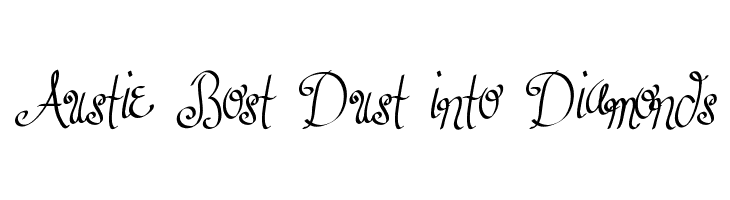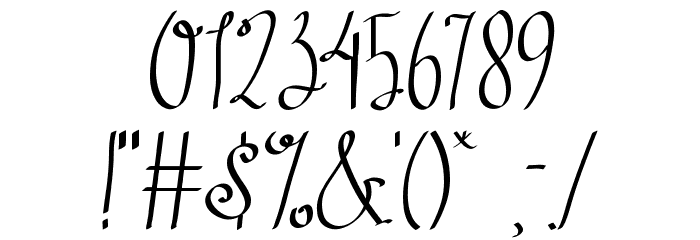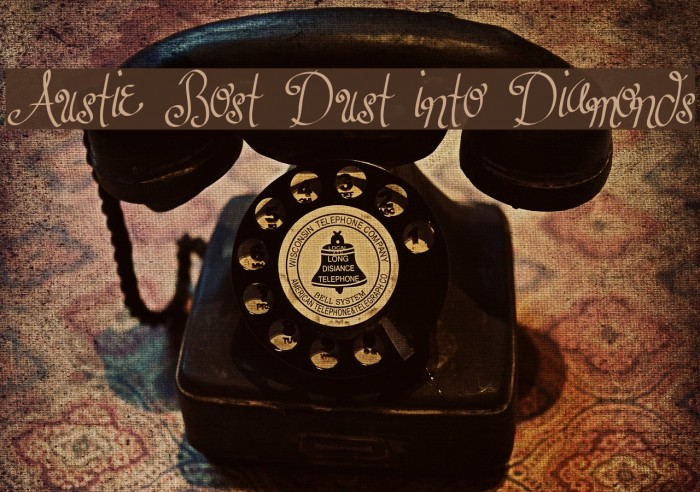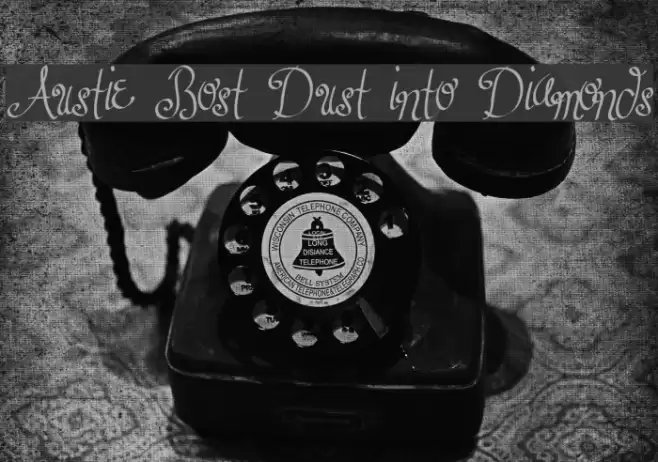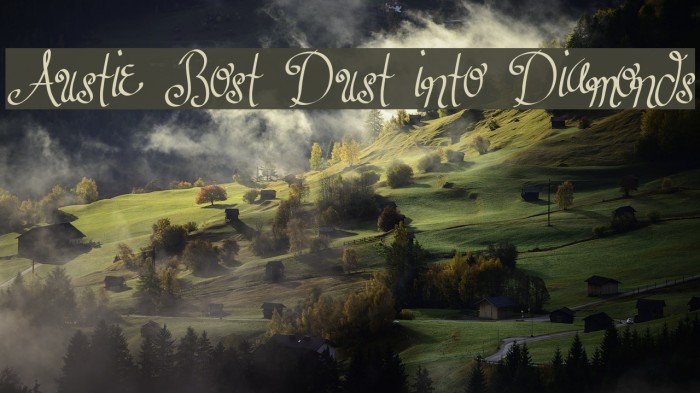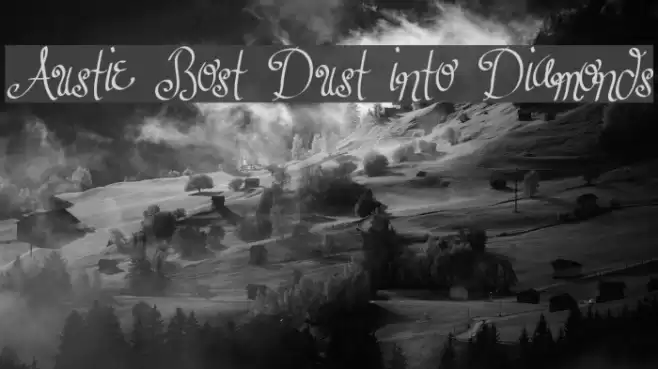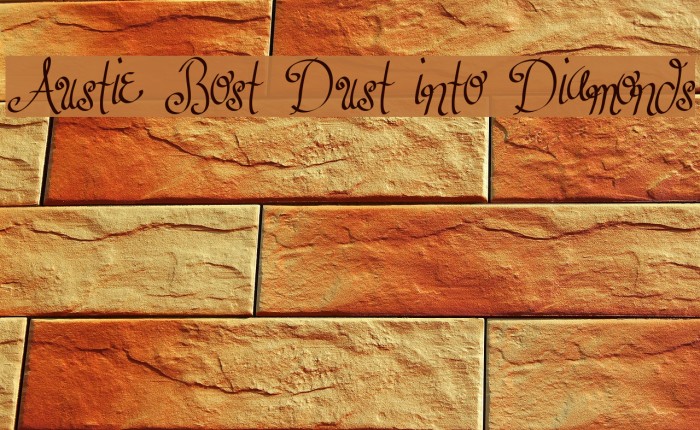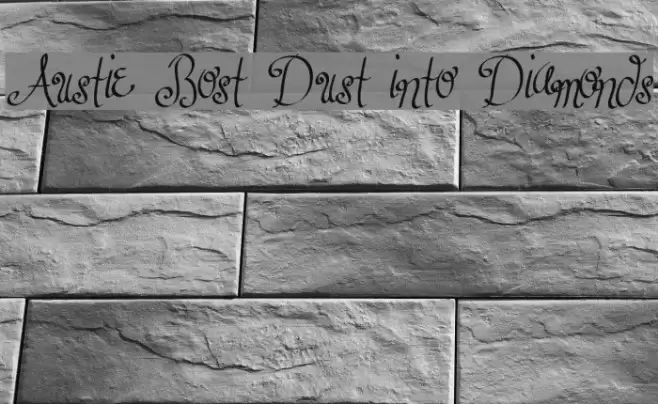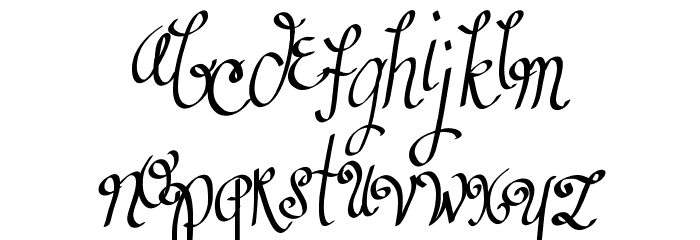
Austie Bost Dust into Diamonds Font
✎ Curly
| Kategorien | Curly |
| Anwendungsfall | Headlines, Logos, Invitations |
| Vorgeschlagene Projekte | Ideal for wedding invitations, greeting cards, playful branding, and artistic posters. |